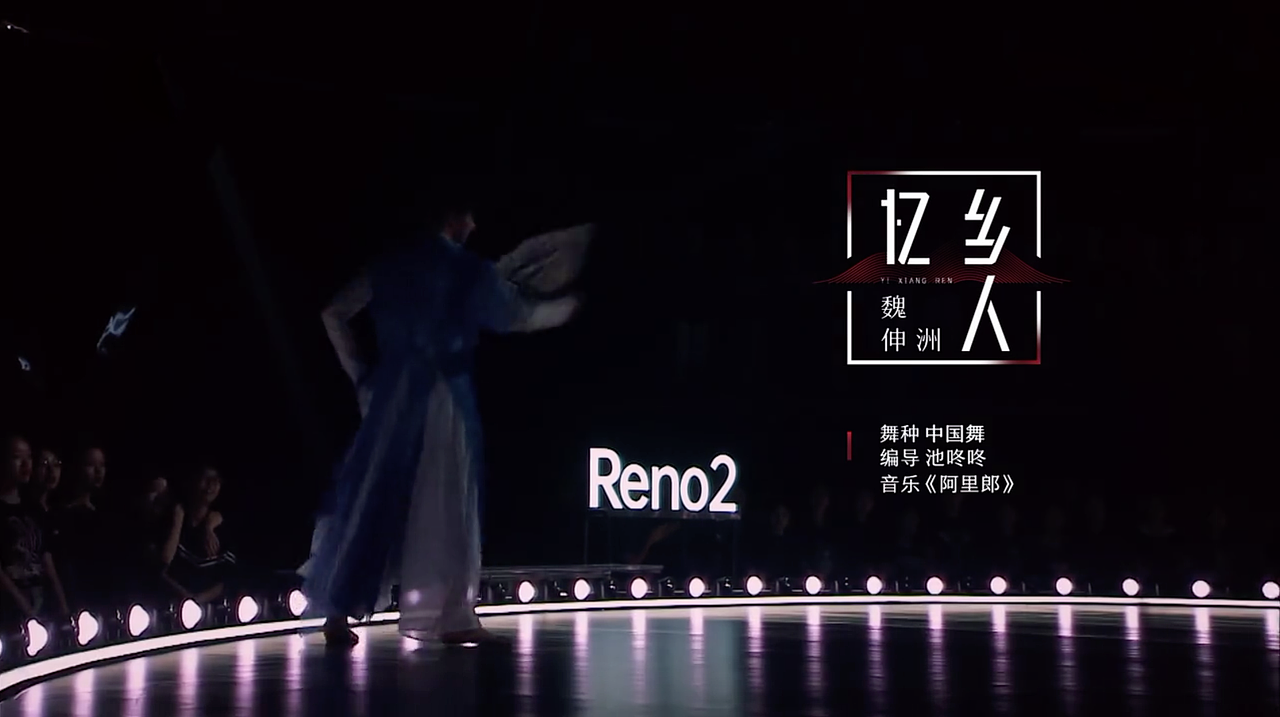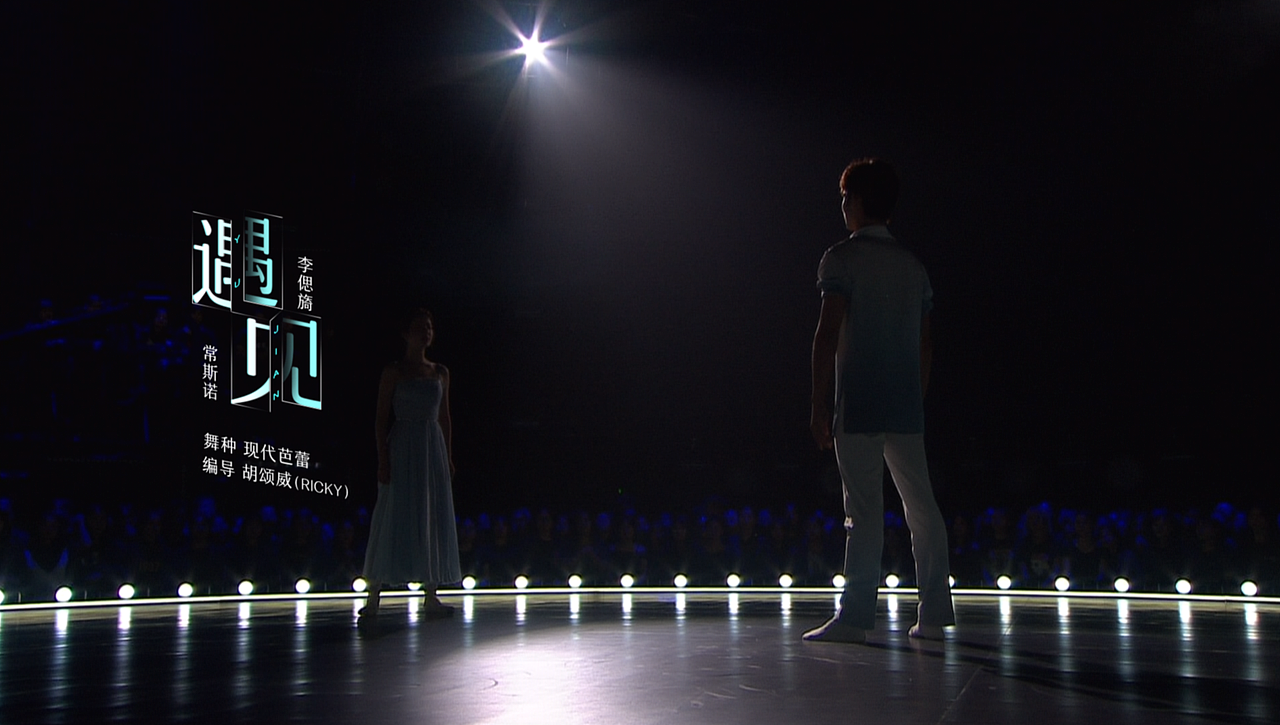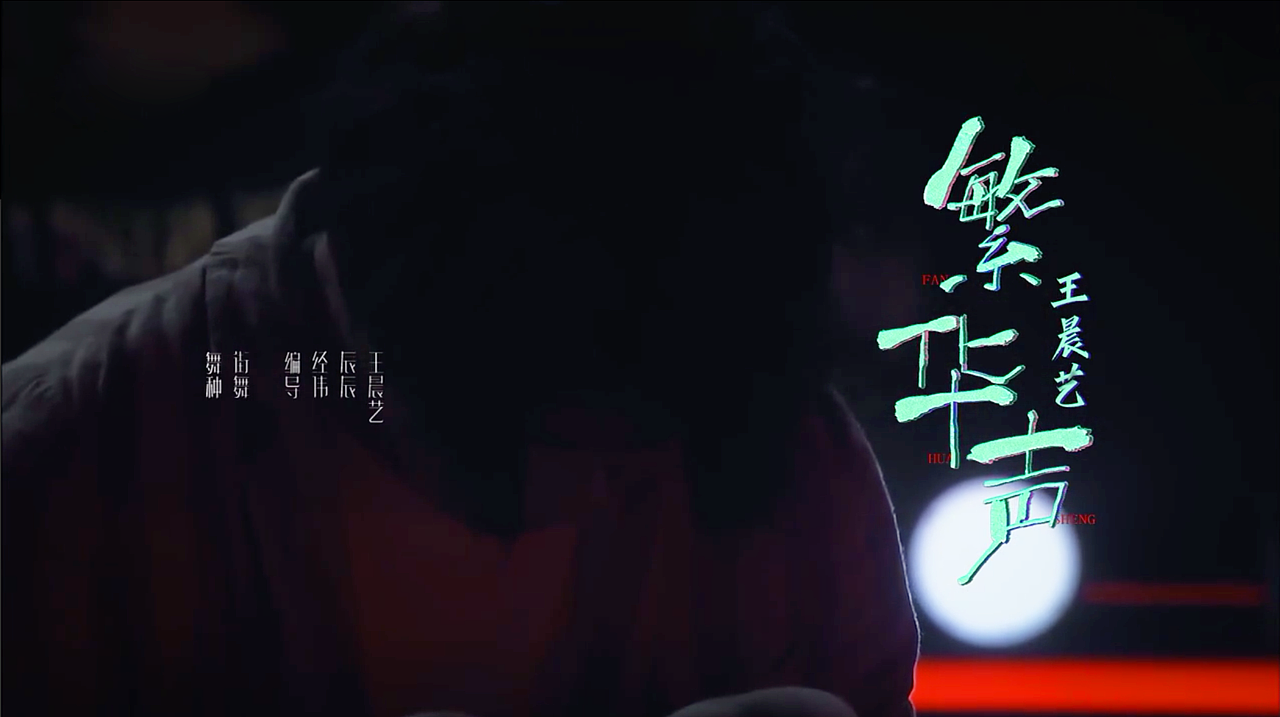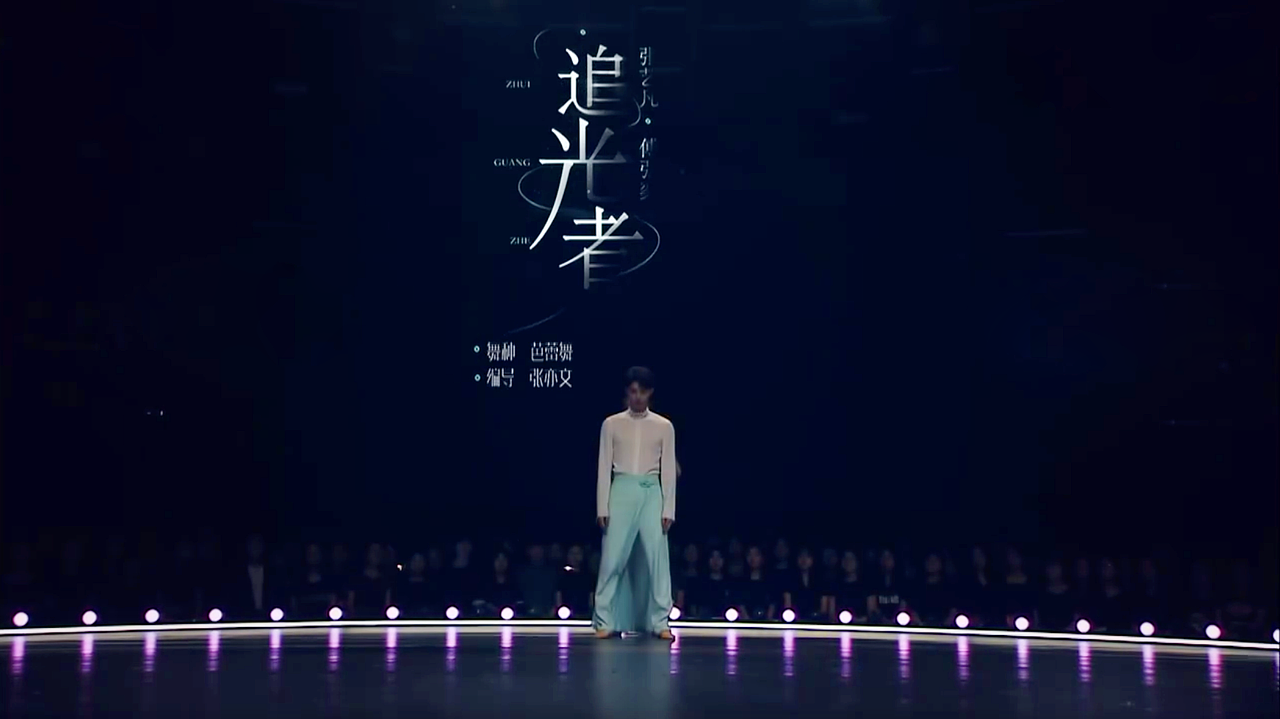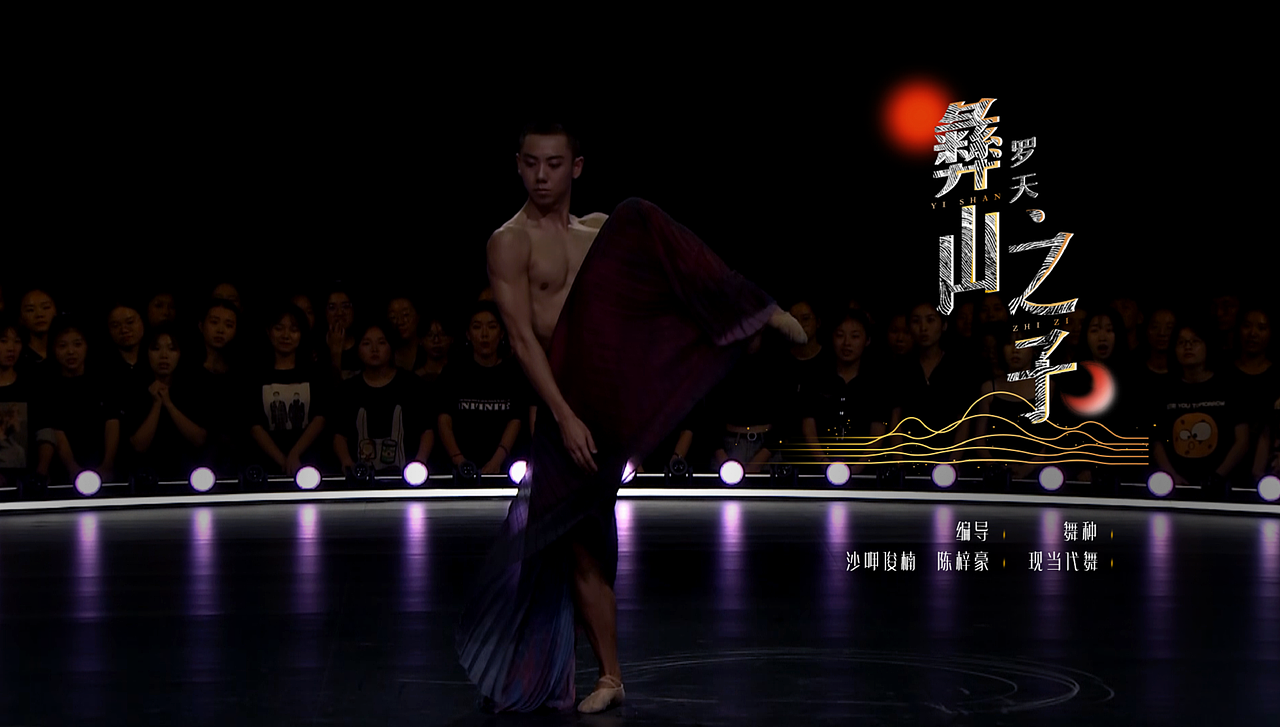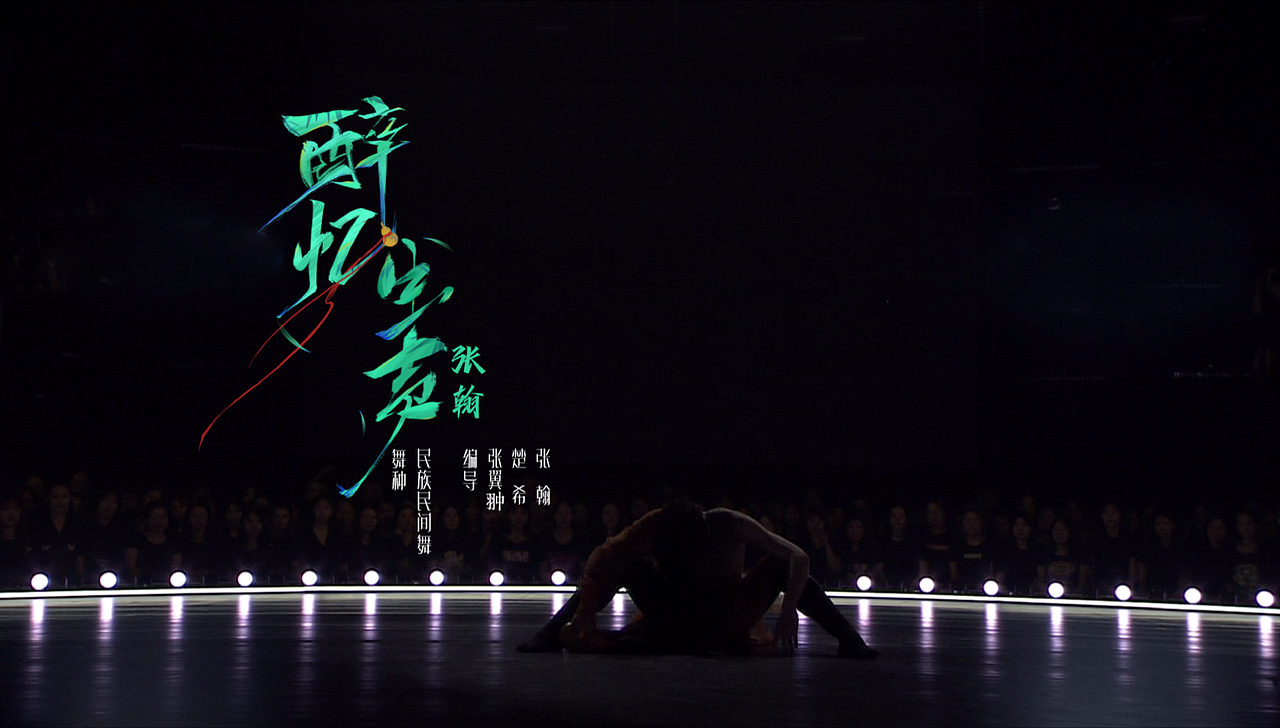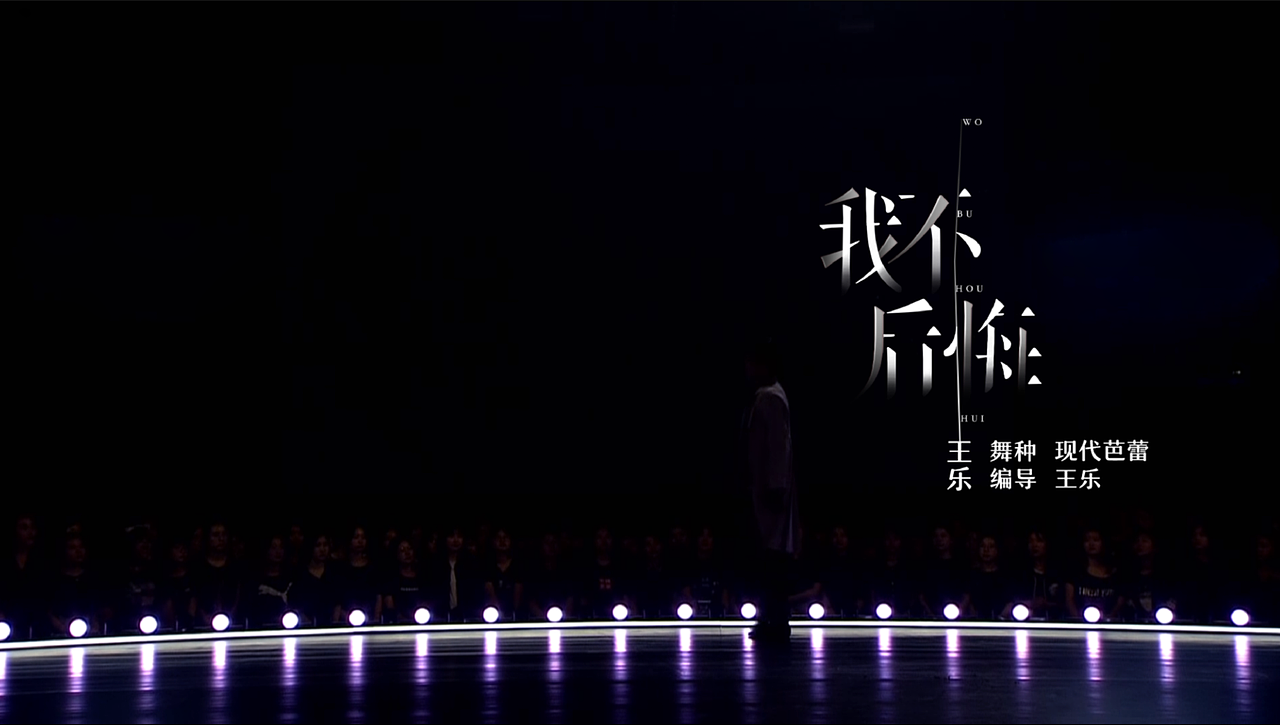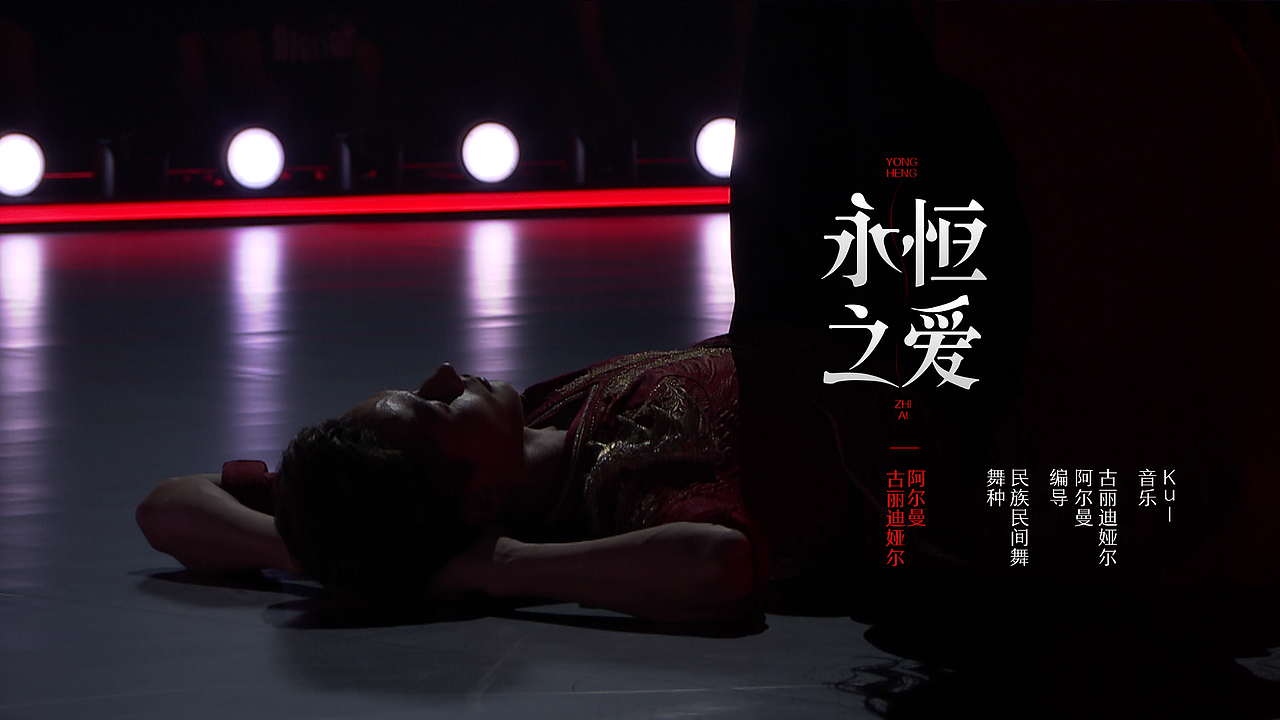
湖南卫视2019《舞蹈风暴》舞蹈名
《舞蹈风暴》的制作团队来自热门音乐竞技节目《歌手》,有种是舞蹈版《声入人心》。第一、二期已经播出,反响不错,在这里整理出舞蹈名的设计加一些觉得还不错的舞名设计,还有第一期做的几个意境测试,分享给大家。我门这次舞名设计用了大量手写、书法体,得意于我们有书法爱好者,真的挺不错的。
第一期的舞蹈名不想做常规,就是一个舞名设计,所以我们挑选突出的舞者做意境画面,但是考虑到各种因素,还是想单纯突出舞者,所以去掉了这个想法。
上屏版本
测试版本
上屏版本
测试版本
上屏版本
很多舞蹈名设计大部分是根据舞种的风格,舞者的风格来设计字体的。
每期的量其实还挺多的,都要单独设计字体,还要规避一些同一期舞名设计的同色,同风格,着实对于我门来说难度不小。高要求的导演组,也同时对自己的高要求做出了这些美丽的舞蹈名!为自己点赞!
上屏版本
第二期磨出了很多作品出来,应该是掉了很多头发,哈哈,这是上屏版本。